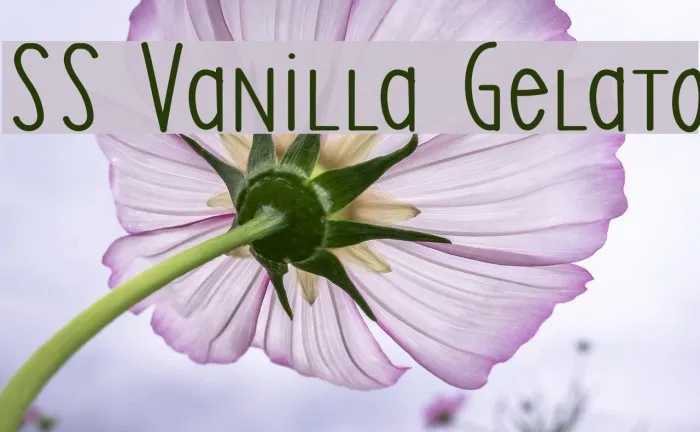
SS Vanilla Gelato Font – Fonte Grátis
SS Vanilla Gelato Font
A fonte SS Vanilla Gelato Font é uma evolução do famoso estilo limão sem gosto, Lemonberry Sans. Sabrina Schleiger criou a SS Vanilla Gelato para oferecer um aspecto mais suave e charmoso ao design de letras manuscritas. Com suas curvas suaves e texturas interessantes, esta fonte é perfeita para decorar qualquer projeto de arte digital que você esteja criando. Ela possui um estilo retrô e fresco ao mesmo tempo, uma mistura exata do que tanto os entusiastas quanto os designers buscam em uma fonte manuscrita. Esta fonte é gratuita para uso pessoal, mas se você planeja usá-la comercialmente, será necessário adquirir uma licença. Com a SS Vanilla Gelato Font, adicione um toque de delicadeza e elegância ao seu próximo projeto gráfico!